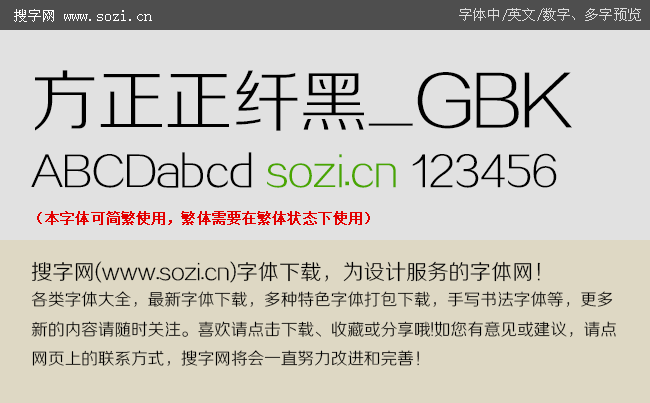
方正正纖黑_GBK
搜字網(wǎng)提供方正正纖黑_GBK中文藝術(shù)字體下載,正黑體取傳統(tǒng)黑體結(jié)構(gòu),筆形全部采用平行、垂直與弧度的流線形設(shè)計(jì),簡(jiǎn)潔易識(shí)、美觀大方,具有個(gè)性,加之鏡像對(duì)稱的現(xiàn)代構(gòu)成形式,達(dá)到莊重與簡(jiǎn)潔有機(jī)融合、設(shè)計(jì)感與閱讀功能兼?zhèn)涞淖罱K效果。適合書(shū)籍排版,報(bào)紙排版,海報(bào)設(shè)計(jì),包裝設(shè)計(jì)等廣告設(shè)計(jì)場(chǎng)合應(yīng)用。